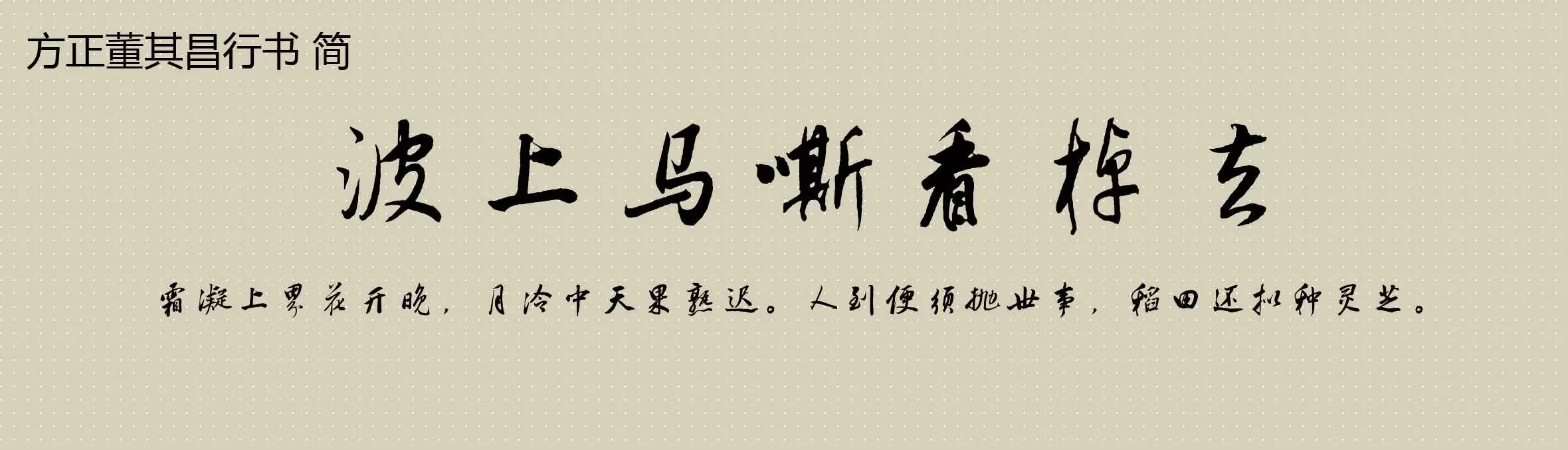
方正董其昌行书以董其昌书法作品《酒德颂》、《濬路马湖记》、《岳阳楼记》、《麻姑仙坛记》等书法作品为主要临创开发依据,并选用了大量的原帖字形,保留和延续了其笔画圆劲秀逸、平淡古朴及字体飘逸空灵、风华自足的特点。适合应用于电商、品牌、海报、杂志、书籍、包装、广告、招牌、新媒体、影视、动漫等。
董其昌(1555~1636),字玄宰,号思白、香光居士。明后期大臣,曾官至南京礼部尚书与太子詹事,去世后获谥“文敏”。画擅山水,书法出入晋唐,自成一格,又颇能诗文。书画诗文传世佳作颇多。其书画风格与书画理论对后世亦颇具影响。